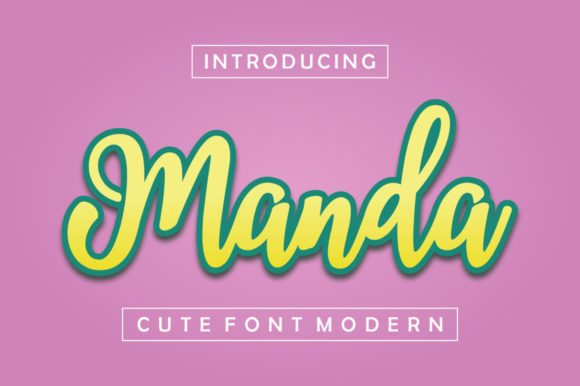
Manda Font Font
Manda Font – خط احترافي أنيق
استمتع بالأناقة والبساطة مع Manda Font، الخط المثالي للتصميمات الإبداعية والمشاريع الاحترافية. يتميز هذا الخط بتصميمه العصري وسهولة قراءته، مما يجعله مثاليًا لاستخدامه في الشعارات، والعلامات التجارية، والتصميمات الطباعية، والمطبوعات الرقمية.
???? مميزات الخط:
✅ تصميم أنيق وعصري يناسب مختلف الاستخدامات
✅ يدعم الحروف الكبيرة والصغيرة لتنوع في التنسيق
✅ مثالي للعناوين، الشعارات، والمحتوى الإعلاني
ارتقِ بتصميماتك مع Manda Font وأضف لمسة من الاحترافية والإبداع إلى أعمالك! ????